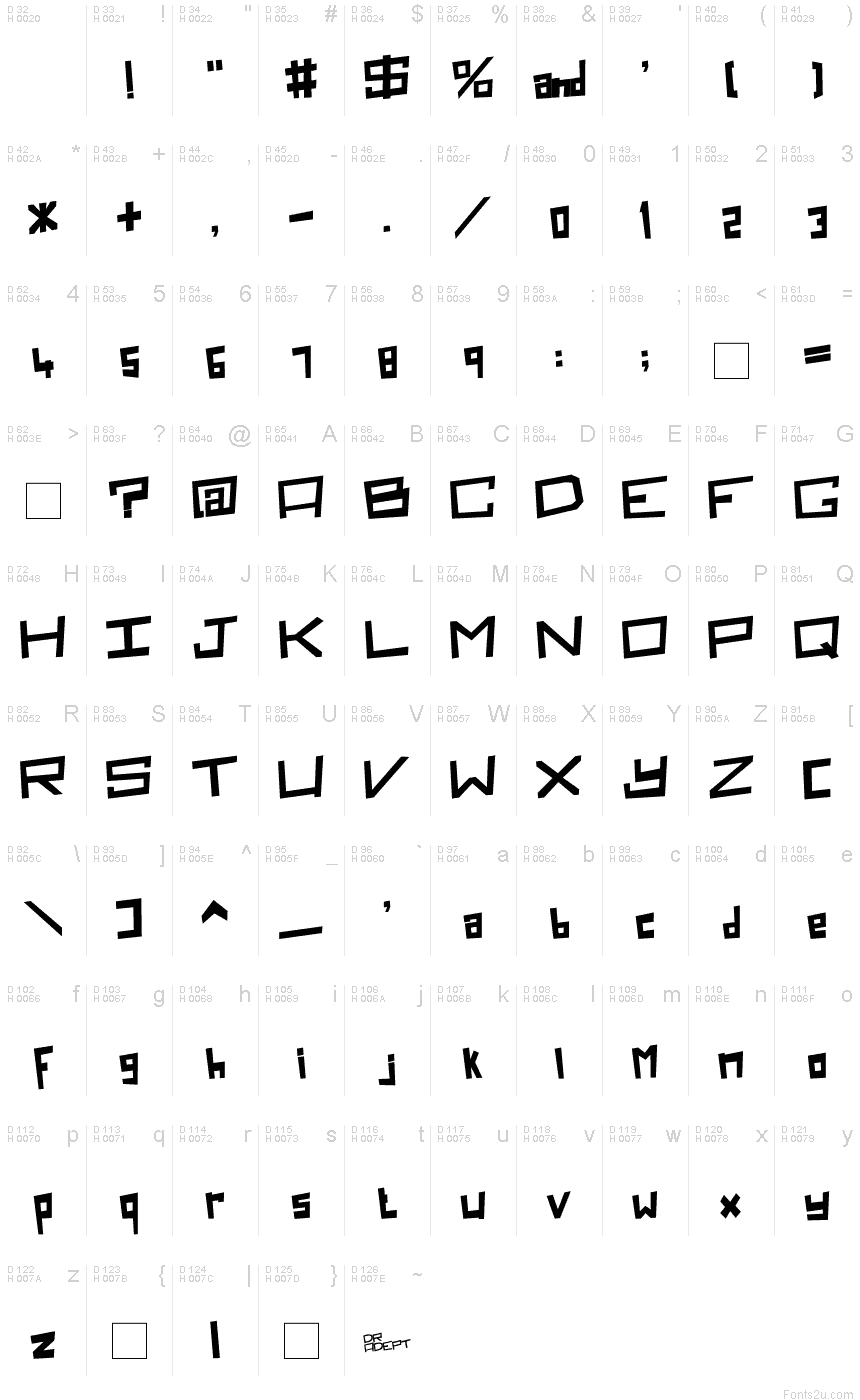
<p>Il font Box Clever presenta uno stile massiccio e inclinato, dal carattere giocoso e artigianale; ogni lettera si inclina con un'angolazione diversa, come pezzi di un puzzle scomposto. Le forme piene e gli angoli netti gli conferiscono un'energia da fumetto, pronta per i poster, che salta subito all'occhio: è l'ideale quando vuoi che la tipografia si faccia sentire. È un font gratuito che punta su un ritmo audace e irregolare per titoli di grande impatto.</p><p>Questo font gratuito funziona particolarmente bene per copertine di libri per bambini, branding creativo, titoli di giochi, inviti a feste, adesivi e grafiche audaci per i social media. Box Clever dà il meglio di sé nelle dimensioni grandi, dove i suoi contorni stravaganti e il suo aspetto irregolare possono davvero respirare. Per i testi più piccoli, abbinalo a un semplice sans serif per mantenere la leggibilità. Usalo quando vuoi che i tuoi progetti trasmettano un senso di vivacità, informalità e un pizzico di malizia.</p>